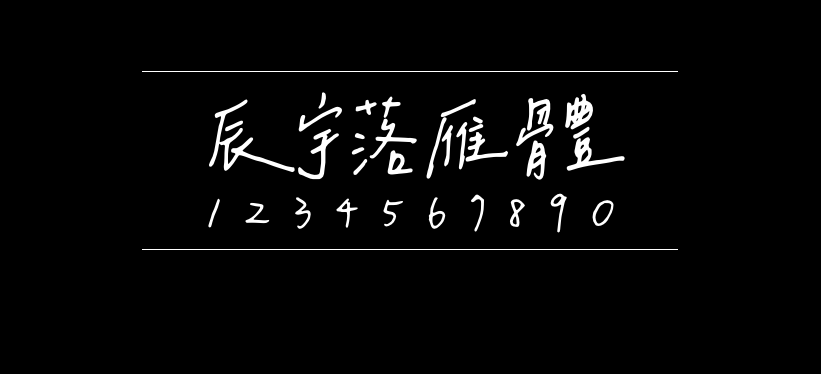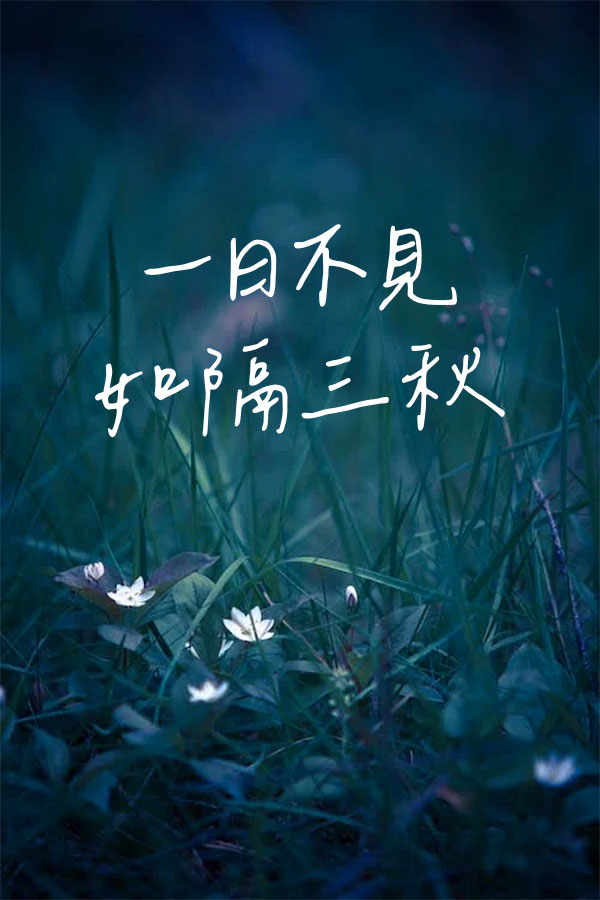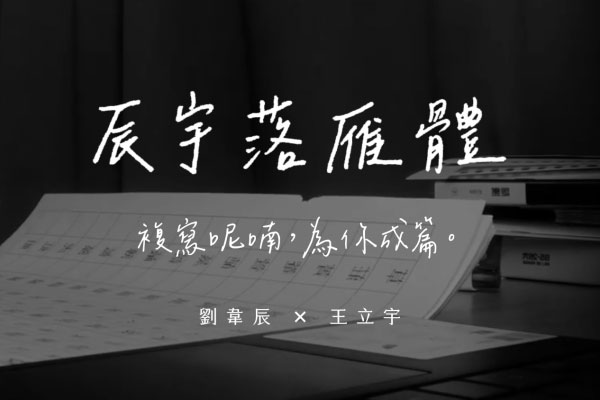
辰宇落雁体
辰宇落雁体(辰宇落雁體)是中国台湾网友刘韦辰 和 王立宇合作创作推出的一款免费商用开源字体,在Github上采用SIL Open Font License 1.1授权发布,您可以免费用于个人和商业用途。
辰宇落雁体是一款原子笔手写风格字体,适用于各种需要手写个性化的场合。
【辰宇落雁體】── 複寫呢喃,為你成篇
「辰宇落雁體」是我與韋辰在學校的自主學習計畫,由韋辰負責書寫,我進行後製而成。手寫字型就像是我們將字詞複寫於紙上,讓字跡留下,以這種近似雋永的形式封裝,使被複寫的日常沒有保質期,也像是一種永恆的召喚,在任何無法抵達的以後,都能為你書寫成篇。
製作故事
欸,你要不要做手寫字體?
去年的八月,那陣子我開始關注字型相關議題,在一次偶然看到韋辰的手寫字後,萌生出要是自己也能做一套手寫字體,真是太酷了!而適逢 108 課綱的我們,課綱強調自主學習的精神,正巧讓我們有機會發展計畫,於是,手寫字體的鑽研之路就這樣開始了⋯⋯
但「萬事起頭難」,我們一開始的起步並不這麼順利,對於字型不太熟悉的我們於是開始搜尋相關資訊,忽而地想到,YouTube 頻道「壹加壹」與 justfont 推出的粒線體,我們寫信請教手寫字型的前期製作方向,獲得了他們真誠的回覆,他們向我們分享製作字型需注意的要點,也在計畫過程中提供我們諮詢與技術指導,成為很大的助力。
我們最初是在線上字型製作平台──「守寫字網站」習得手寫字型的製作流程,後來為了更大程度的製作自由,我們嘗試拆解流程,並以自己的方式進行製作,然摸索的過程並非一蹴可及,在那段期間的每週四,我潛心鑽研的同時,韋辰就在一旁書寫,兩個人窩在圖書館的角落為心中的理想並肩努力著,製作字體是枯燥的,日復一日的書寫、修改與後製,現在想想,我們還挺浪漫的,為了完成理想,不惜代價的繞了點路,也有好幾次洩氣的想著,或許真的做不出來了,是對於成果的想像才讓我們堅持下來。
在字體做出成果後,也陸續獲得不少稱讚,神奇的是,製作過程中並未覺得特別的我們,在第一次打出完整的句子時,卻被感動了。若浪漫一點來說,製作手寫字體這件事,似將字詞複寫於紙上,將字跡留下為人使用。
回想製作的契機,那句「欸,你要不要做手寫字體?」在今天終於實現了,韋辰寫下這些文字後也將與十六歲告別,正所謂字如其人,期望她未來回首,能在字裡行間看見自己。
其他可能
其實,我們在計畫一開始製作的字體是以 Pentel Touch 書寫的粗體字,但因為製作目標與後期調整較為複雜,在稿紙書寫完成後,遲遲未能釋出字型。而我們隨後也製作了原子筆書寫的版本,也就是現在的「辰宇落雁體 Thin」。
辰宇落雁体对繁体支持得不错,日常使用基本不缺字,简体支持得相对弱一些。还是比较适合繁体的场合。